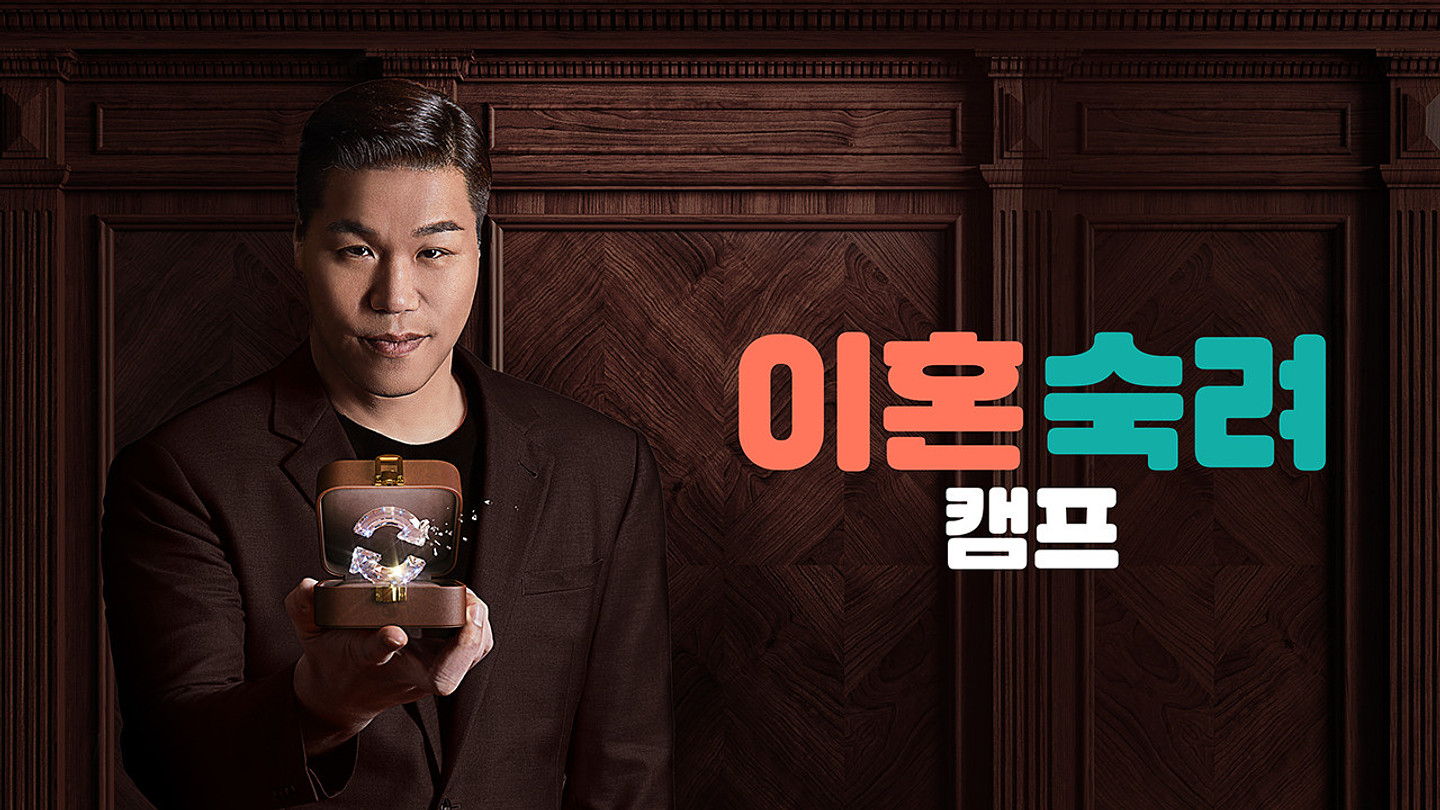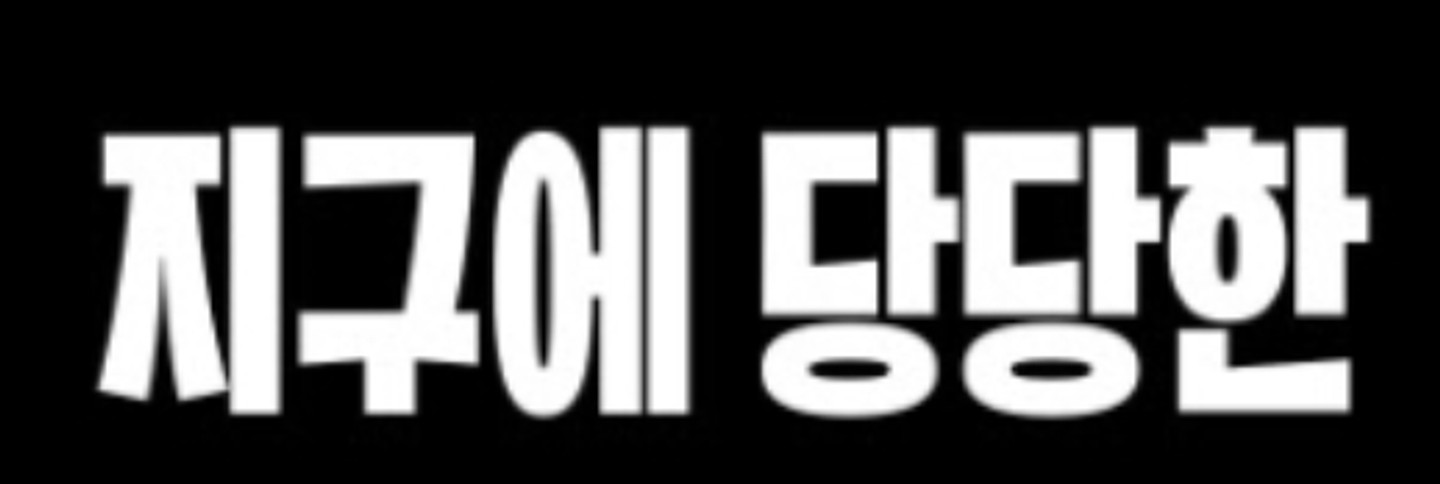
어느 광고 기획서 PPT에 들어간 폰트입니다. 이 이미지 속 문장은 모두 같은 폰트로 이루어져 있는 것 같은데, 어떤 폰트인지 아시는 분 있나요??
안녕하세요 고객님이 이 폰트를 요청하시는데 잘 모르겠습니다 도와주세요 배민 글씨같기도 하고 잘 모르는 글씨체 입니다 혹시 비슷한 글씨라도 아시면 고수님들 공유 부탁드립니다
궁금해서 밤에 잠이 안옵니다;; 폰트 찾기 전문가님들 제발 찾아주세요!!!! J와 I 가 가로획이 들어간 고딕인데 폰트입니다. 모든 폰트 사이트(산돌구름,WhatTheFont,Adobe font 등) 2일 동안 다 찾아봤습니다. 정확히 저 조건에 부합하는 폰트를 못찾겠습니다. 그나마 제일 비슷한 폰트는 'Kometa' 인데 J가 다르더군요 ㅠㅠ 부탁드립니다~~!!